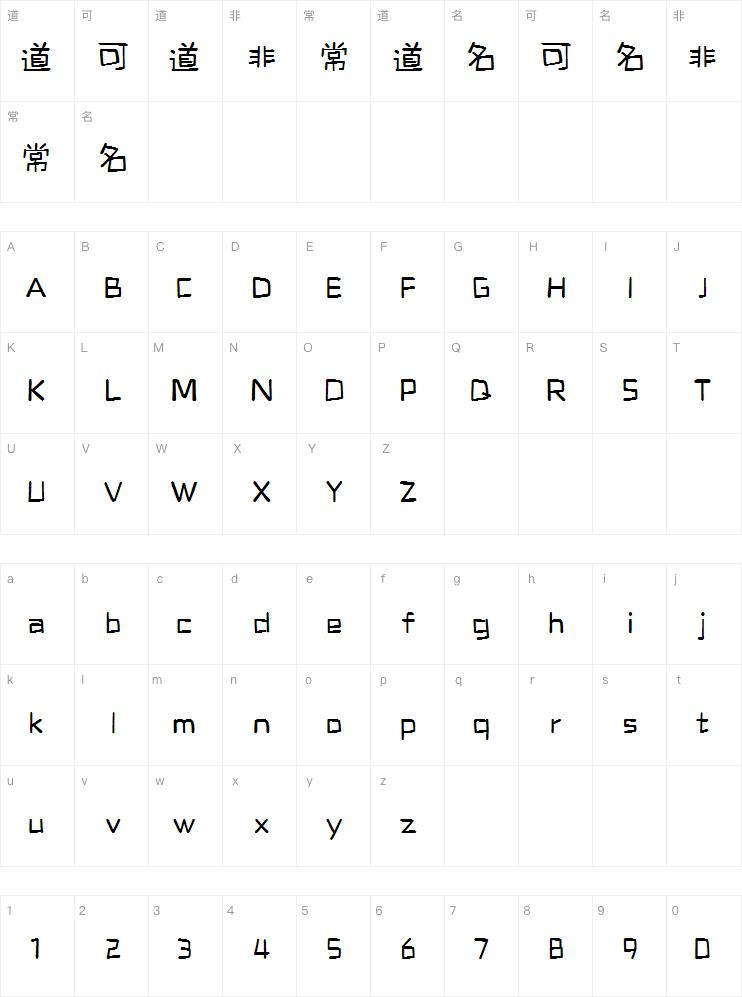
上首童真体
上首童真
上首童真体,简体中文约6763字,在笔画特点上,线条圆润柔和,笔画粗细不均的呈现,意在模拟儿童手写笔记的特点。结构布局上,字间距和笔画之间的疏密不一,营造出了一种轻松、自在的感觉,在重心上,我们打破了传统字体追求重心稳的规则,这样为字体增添了动感活泼的视觉效果。童真体的设计旨在捕捉儿童天真无邪、活泼灵动的特质,将其融入到字体的形态之中,唤起人们内心深处对童年纯真时光的美好回忆和情感共鸣。适用于搭配标志、广告标语、商业广告等高端属性。